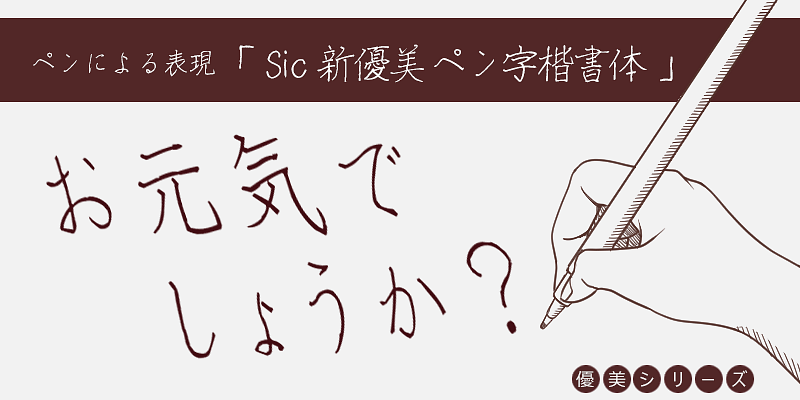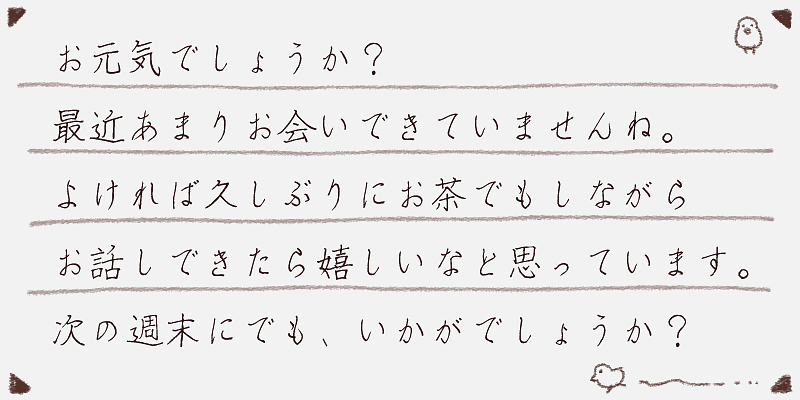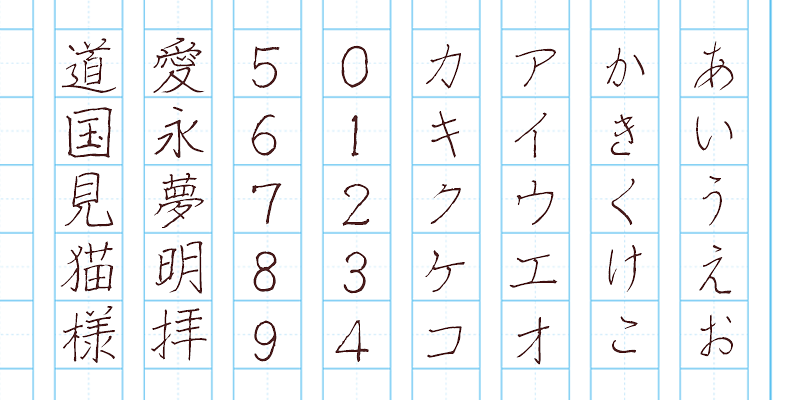
Eiichi Kawazoe studierte schon in jungen Jahren Kalligrafie unter Anleitung seines Vaters. In der Kalligrafie-Abteilung der Universität lernte er Kanji von Kiseki Kosaka und Toson Amaishi sowie Kana von Kitsunan Tanibe und Kayu Hirata. Um die fließende japanische Kalligrafie von Kanji und Kana weiterzuführen, die mit Yukinari begann, sammelte er zahlreiche alte Dokumente. Er verfeinert seine Fähigkeiten kontinuierlich, um die traditionellen japanischen Schriftzeichen zu bewahren, die sich parallel zu Ukiyo-e entwickelten. Er gestaltet außerdem Schreinsiegel und Rakugo-Titelkarten und wagt sich an den Schriftzeichen aus Sumo und Kabuki.